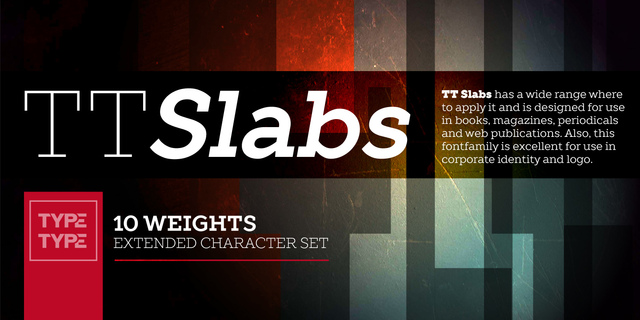
Миру нужны красивые, простые и качественные шрифты. Нам нужны простые и геометрические шрифты. Сляб – это форма засечек, которая и дала название гарнитуре. Если вы ищете универсальный шрифт с широкими пропорциями для ваших проектов — Slabs идеально подойдет вам. Область применения: пищевая упаковка, упаковка бытовой техники, газеты, журналы, заголовки, вывески, декорации, логотипы, дизайн интерьера магазинов, фруктовые и овощные этикетки, ценники, гравировка. Оптимизированная для веб-сайтов, мобильных приложений и печатных материалов. Шрифт разработан Иваном Гладких в 2014 году.
Ассоциации c начертанием TT Slabs Black ItalicКачества и характер:
заметный, яркий, активный, броский, точный, модный, деловой, устойчивый, стабильный, статичный, твердый, серьезный, ровный, прямоугольный, железный, стальной, надежный, уверенный, сильный, индустриальный, техногенный, убедительный, авторитетный, внушительный, мощный, тяжелый, военный, армейский, мотивирующий, ответственный, суровый, громкий, крутой, резкий, острый, четкий, амбициозный, сексуальный, спортивный
электростанция, энергетика, завод, архитектура, блокбастер, боевик, экшен, мотор, двигатель, конструктор, техника, промышленность, станок, инструмент, политика, власть, машиностроение, тренажеры, армия, ремонт, охрана, защита, страйкбол, полиция, обувь, грузовик, дальнобойщик, сталевар, технологии, футбол, спорт Стилистика: